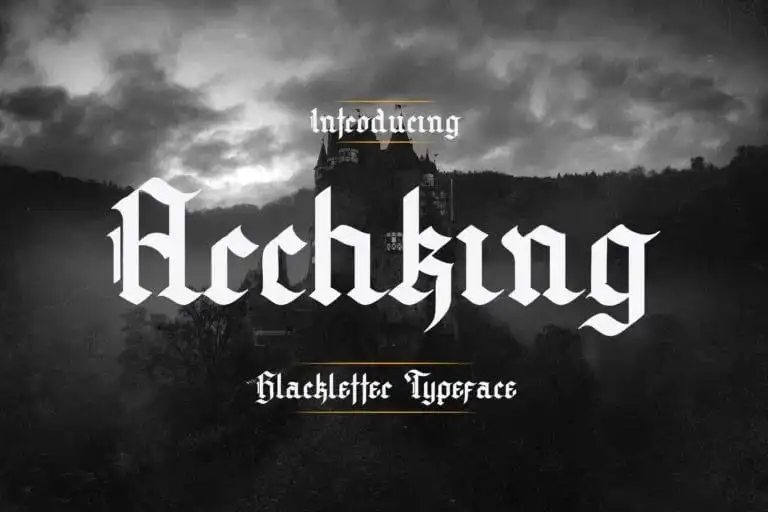
Archking Trial Blackletter Font – Download Grátis
A Archking Trial Blackletter Font é uma escolha ótima para designers que desejam adicionar um toque único a seus projetos visuais. Esta fonte blackletter organic, criada e compartilhada pela typefactory, traz uma sensação de desenho manual. Ela inclui detalhes ornamentais extra que dão ao texto um ar ainda mais autêntico e intrigante. Com a Archking Trial Blackletter Font, você pode explorar inúmeras possibilidades criativas. Desde produtos logo, posters e lojas de barbear até headlines, embalagens e cartões de casamento, esta font oferece uma solução versátil para diversos tipos de projetos. Através da sua design exclusivo e arteanal, a Archking Trial Blackletter Font se torna um recurso indispensável tanto para designers profissionais quanto para amantes do desenho manual em seu trabalho gráfico.